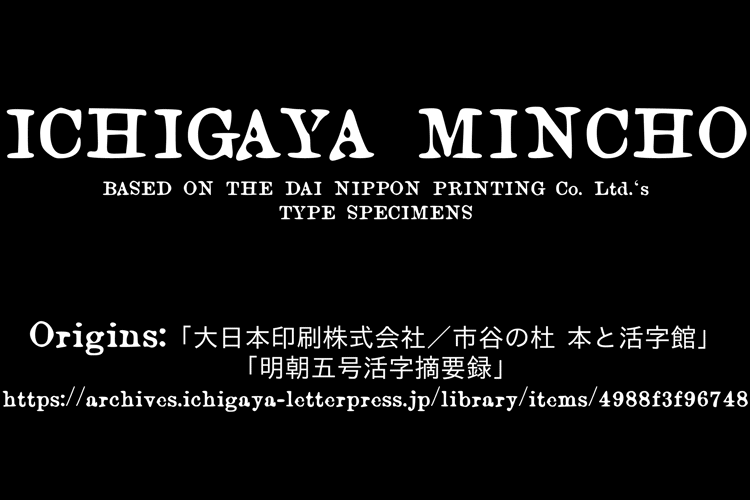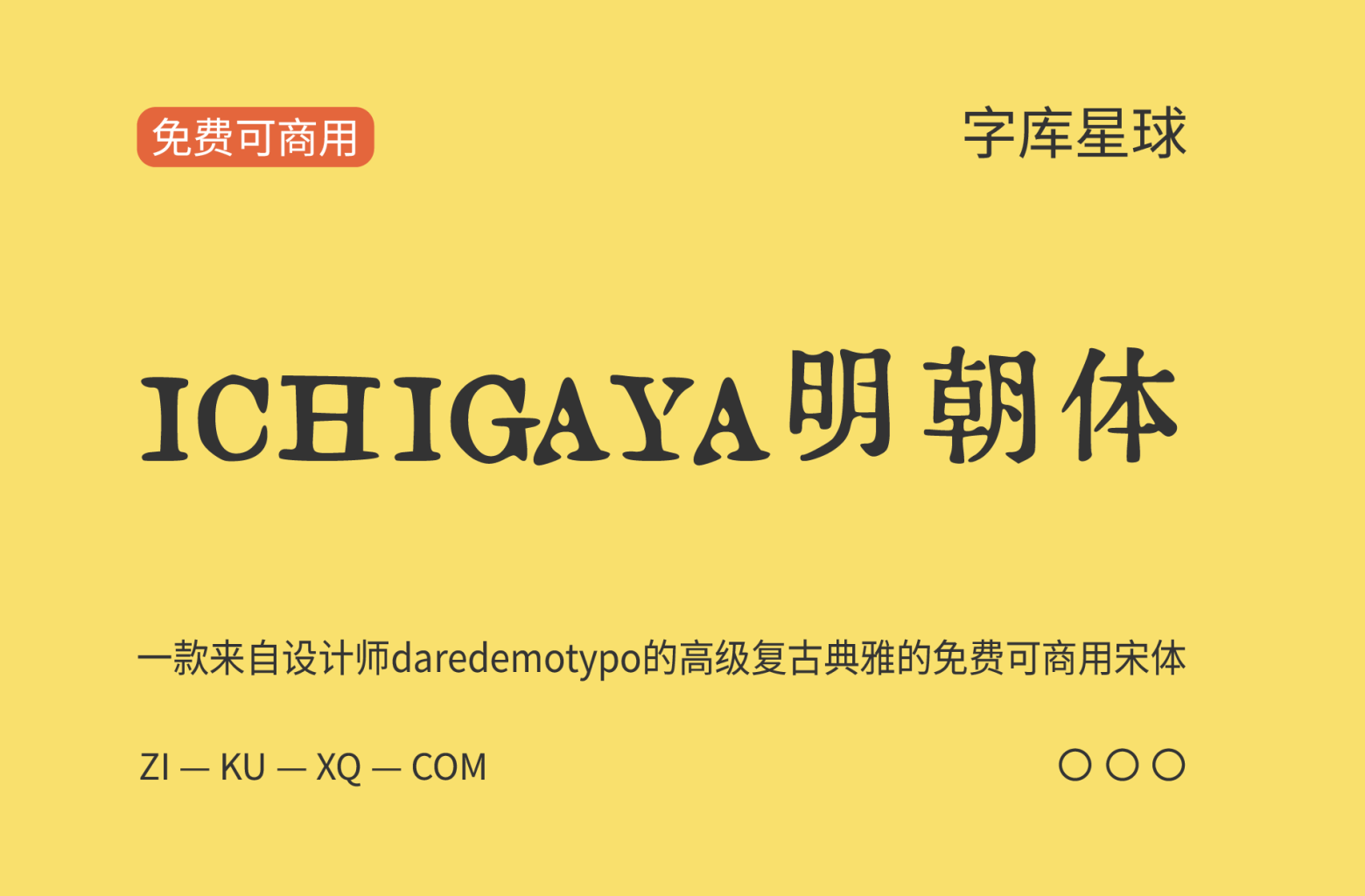
ICHIGAYA明朝体
ICHIGAYA明朝体(ICHIGAYA Mincho)是一款来自设计师daredemotypo的高级复古典雅的免费可商用宋体
他使用InkScape的自动追踪功能将大日本印刷的前身企业秀英舍活版制造所的活字制作成字体。 大部分以市谷杜本和活字馆所有的《明朝五号活字摘要录》(1913年)为基础。